Diseña una tipografía digital de la A a la Z
Juanjo te explica cómo diseñar ydesarrollar tipografía digital desde el boceto inicial hasta su uso en cualquier proyecto.
La vida de Juanjo López (@juanjez) gira en torno a las letras; es diseñador de tipografías y tipógrafo y además, también pasa buena parte de su tiempo haciendo lettering. Aunque sus trabajos suelen tener un estilo que recuerda mucho a las tipografías antiguas, con un marcado sello artesanal, Juanjez abraza la tecnología, que le permite crear una tipografía en mucho menos tiempo y con medios más asequibles que si prescindiera de ella. Y es precisamente eso lo que enseña en el curso que imparte en Domestika, Diseño de una Tipografía digital de la A a la Z, a crear tu propia tipografía para utilizar en cualquier tipo de proyecto digital.
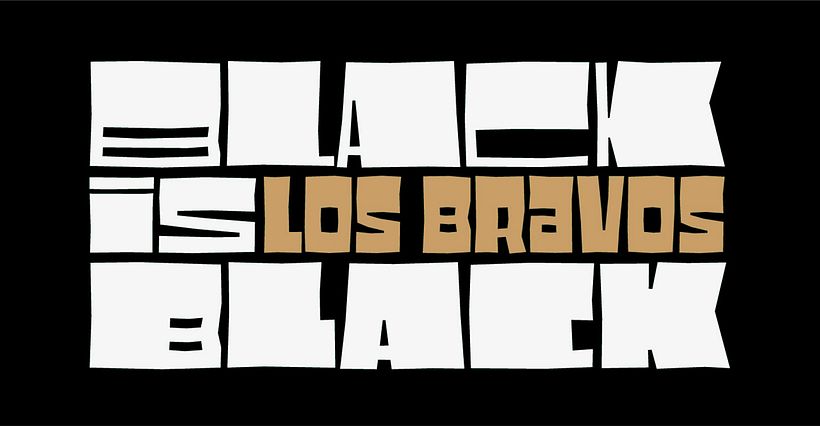
El que propone Juanjez en este curso es un recorrido por todo el proceso de creación de una tipografía digital, que comienza con una idea, que cristalizará en el dibujo de las letras que compondrán tu tipografía. Todas sus fuentes están basadas en conceptos muy potentes y fáciles de adivinar con solo ver los glifos que ha diseñado para ellos. Sin embargo, uno de los puntos fuertes de su trabajo y de este curso, son los consejos que te dará para dibujar las letras para crear tipografías sólidas, aprendiendo a trabajar las formas de las letras y algo tan importante como las curvas de Bézier.
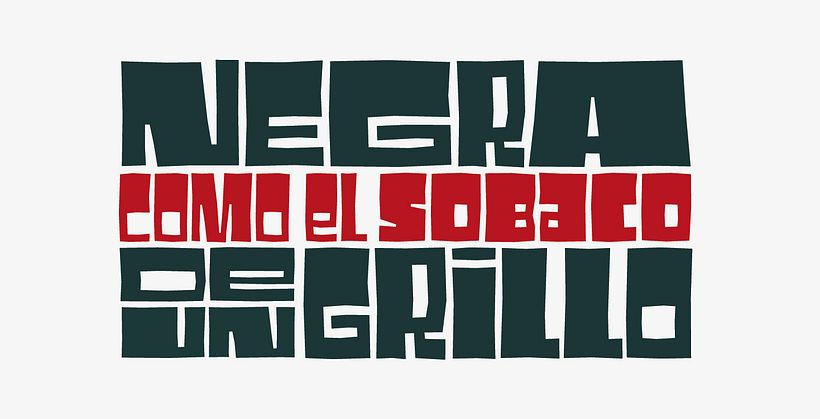
Este es un curso para no iniciados en el diseño de tipografías, por lo que Juanjez te guiará paso a paso por el proceso de creación de tu primera fuente tipográfica; y como se trata de poder utilizar estas tipografías en proyectos digitales, o distribuirlas para que otros puedan utilizarlas en sus proyectos, Juanjez te explicará el proceso de diseño desde un punto de vista digital. Te ayudará a familiarizarte con Glyphs, el software para Mac de diseño de tipografía y producción de fuentes, a trabajar los signos ortográficos, el kerning y a diseñar un especimen atractivo para poder presumir de tipografía.